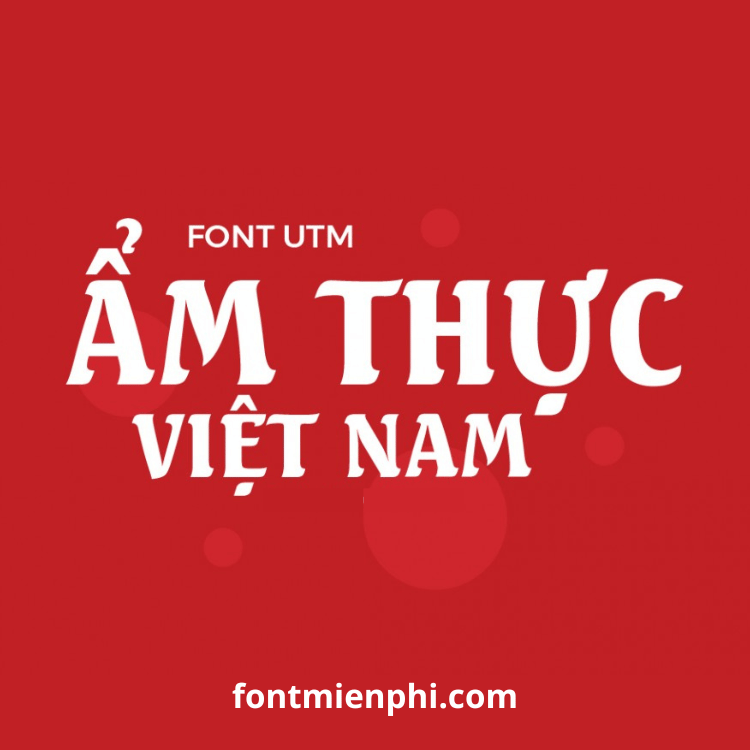
Việt hóa font UTM SeagullBold
Giới Thiệu Font UTM Seagull Bold Việt Hóa
Font UTM Seagull Bold là kiểu chữ sans-serif hiện đại với nét đậm mạnh mẽ, thích hợp cho thiết kế tiêu đề, logo, banner quảng cáo và các ấn phẩm truyền thông. Bản Việt hóa chuẩn hỗ trợ đầy đủ dấu tiếng Việt, giúp designer Việt Nam thoải mái sáng tạo mà không lo lỗi font.
Đặc Điểm Nổi Bật
✔ Hỗ trợ tiếng Việt đầy đủ – Bộ ký tự chuẩn Unicode, hiển thị rõ ràng mọi dấu tiếng Việt
✔ Phong cách hiện đại, chuyên nghiệp – Nét chữ đậm rõ ràng, dễ đọc ở mọi kích thước
✔ Ứng dụng đa dạng – Lý tưởng cho thiết kế logo, bao bì, standee và ấn phẩm truyền thông
Ứng Dụng Thực Tế
Font UTM Seagull Bold Việt hóa hoàn hảo cho:
• Thiết kế logo công ty
• Làm banner quảng cáo
• Thiết kế bao bì sản phẩm
• Ấn phẩm truyền thông, standee